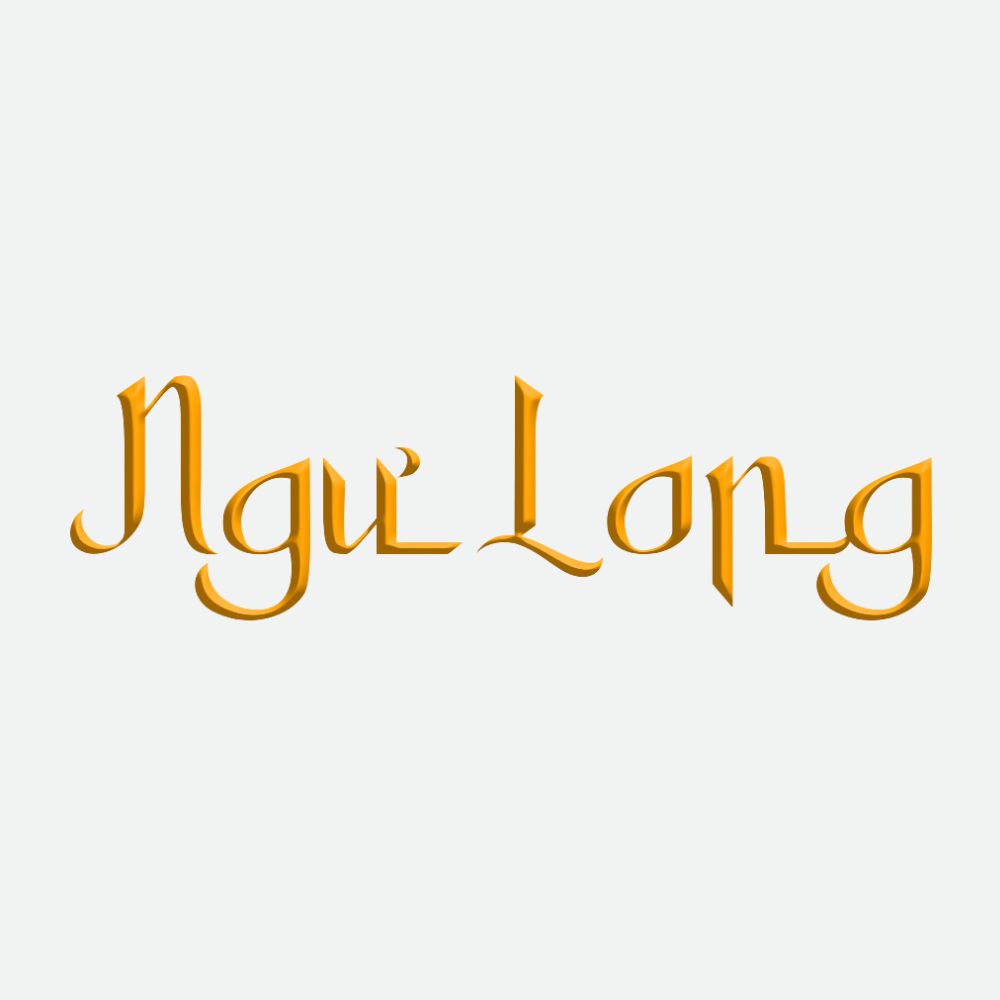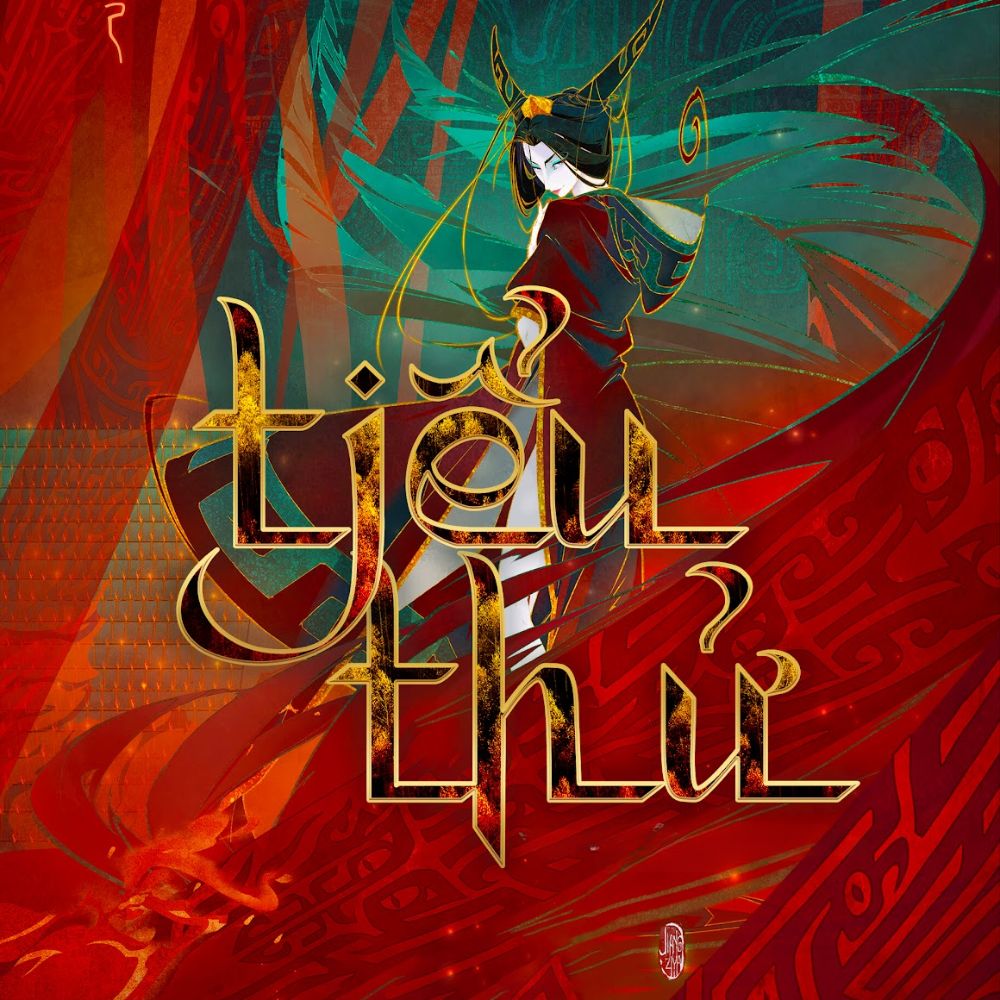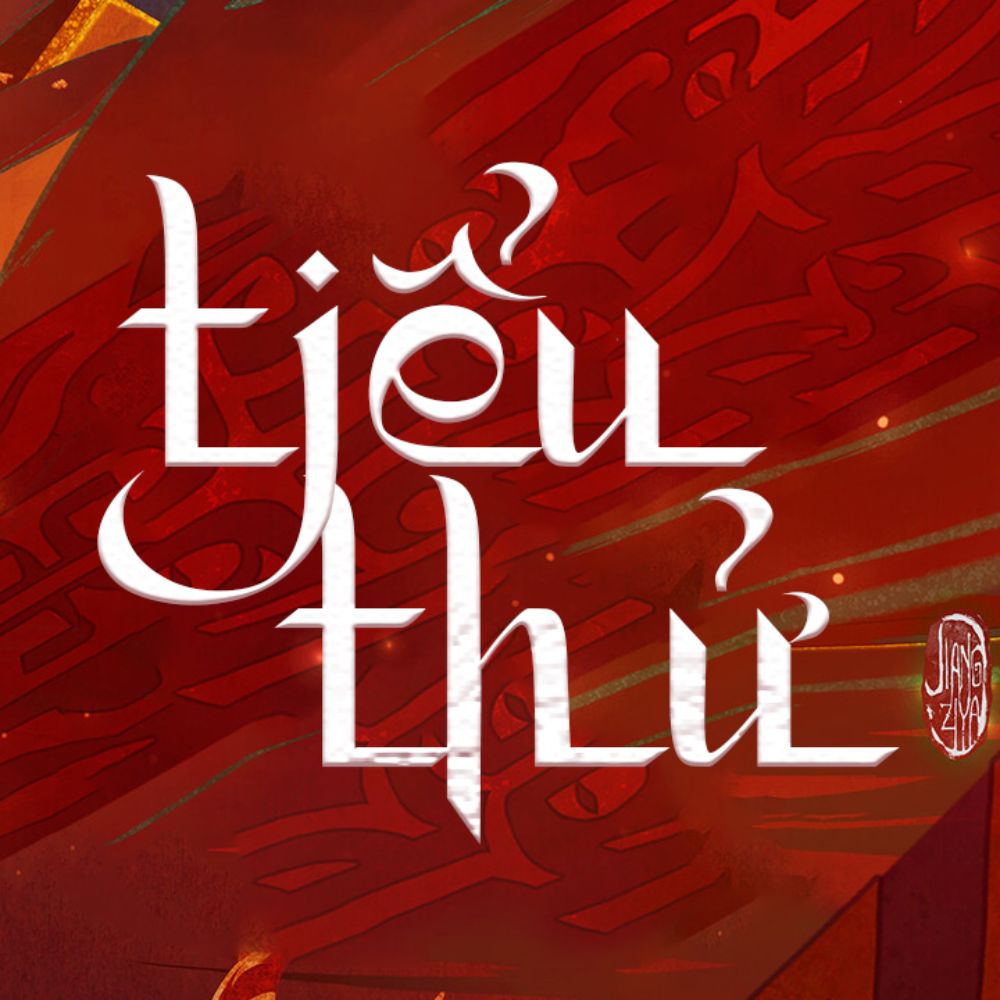
Font cổ trang Việt hóa Zahra là kiểu chữ mang đậm phong cách cổ trang, nổi bật với nét viết mềm mại, uyển chuyển và giàu tính nghệ thuật. Font gợi cảm giác hoài cổ, sang trọng, thường được sử dụng trong các thiết kế liên quan đến văn hóa Á Đông, phim cổ trang hoặc các ấn phẩm mang màu sắc truyền thống.
Đặc điểm nổi bật của font cổ trang Việt hóa Zahra
Font Zahra Việt hóa là kiểu chữ nghệ thuật mang phong cách cổ trang, nổi bật với đường nét mềm mại, uyển chuyển và giàu tính thẩm mỹ. Lấy cảm hứng từ thư pháp Ả Rập, font mang đến cảm giác sang trọng, tinh tế và rất phù hợp cho các thiết kế mang hơi hướng truyền thống hoặc nghệ thuật.
• Phong cách cổ trang, thư pháp với nét chữ mềm mại, bay bổng
• Tích hợp ligature giúp các ký tự kết nối tự nhiên, liền mạch
• Kết hợp nét thanh và nét đậm tạo chiều sâu và sự tinh tế
• Được Việt hóa đầy đủ, hỗ trợ dấu tiếng Việt và glyphs hoàn chỉnh
• Dễ ứng dụng trong nhiều thiết kế cần tính nghệ thuật cao
• Phù hợp làm tiêu đề, thiệp cưới, poster, banner phong cách cổ điển
Font chữ cổ trang Việt hóa Zahra là lựa chọn lý tưởng cho những thiết kế cần sự tinh tế, nổi bật và mang đậm dấu ấn văn hóa nghệ thuật.
Font Zahra Việt hóa mang đậm phong cách cổ trang nghệ thuật
Ứng dụng của font Zahra trong thiết kế
Font Zahra Việt hóa được sử dụng rộng rãi trong nhiều lĩnh vực sáng tạo, đặc biệt là các thiết kế mang yếu tố truyền thống hoặc nghệ thuật.
• Thiết kế poster phim cổ trang, ảnh nghệ thuật
• Làm tiêu đề, slogan cho ấn phẩm truyền thông
• Thiết kế thiệp mời, thiệp cưới phong cách cổ điển
• Trang trí bao lì xì, câu đối, ấn phẩm Tết
• Thiết kế bao bì sản phẩm mang phong cách vintage
• Ứng dụng trong social media, banner, thumbnail
Font chữ cổ trang Việt hóa Zahra phát huy hiệu quả tốt nhất khi sử dụng ở kích thước lớn hoặc làm điểm nhấn trong bố cục thiết kế.
Font Zahra Việt hóa phù hợp thiết kế tiêu đề lớn, giúp bố cục nổi bật và thu hút hơn
Lưu ý khi sử dụng font cổ trang Việt hóa Zahra
Để dùng font Zahra đẹp và không bị lỗi khi in, bạn nên nhớ:
• Nên dùng cho tiêu đề hoặc chữ nổi bật, không phù hợp cho đoạn văn dài vì khó đọc
• Kết hợp thêm font đơn giản để thiết kế dễ nhìn hơn
• Dùng kích thước lớn để thấy rõ nét chữ mềm mại
• Chuyển outline trước khi in để tránh lỗi font
• Kiểm tra lại dấu tiếng Việt trước khi xuất file
• Chọn file font chất lượng để không bị vỡ nét khi in
• Nếu dùng cho mục đích kinh doanh, nên kiểm tra bản quyền
Dùng đúng cách sẽ giúp font Zahra đẹp hơn và thiết kế trông chuyên nghiệp hơn.
Font Zahra Việt hóa với hiệu ứng ligature mượt mà, tăng tính thẩm mỹ cho từng con chữ
Font chữ Việt hóa cổ trang Zahra với hiệu ứng ligature mượt mà, tăng tính thẩm mỹ
Font Zahra phù hợp in trên những sản phẩm nào?
Phù hợp in trên thiệp cưới, bao lì xì, hộp quà, poster, banner hoặc các sản phẩm mang phong cách cổ điển, nghệ thuật.